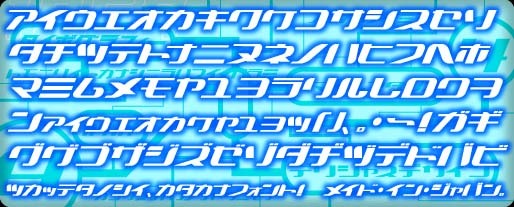
SUMMERCAMPKaSha, un font giapponese gratuito in stile emblema sportivo di Smile Studio e Tohru Fukushima, cattura l'energia del branding delle squadre di fine anni '90. Il set visivo si basa su tratti spessi e inclinati, realizzati con un unico movimento, spesso racchiusi in solidi emblemi ovali, facendo sì che il font appaia più come una collezione di decalcomanie che come una normale scrittura.
Questo rende questo font gratuito una scelta naturale per poster in stile arcade, grafiche streetwear, fanzine di skate, pacchetti di adesivi e titoli che richiedono un impatto rapido e incentrato sul logo. Usalo dove il segno deve parlare da solo — su copertine, etichette di merchandising, volantini per club o brevi titoli — poiché le forme ripetute degli emblemi conferiscono anche alle parole brevi un ritmo atletico, simile a quello di un timbro.